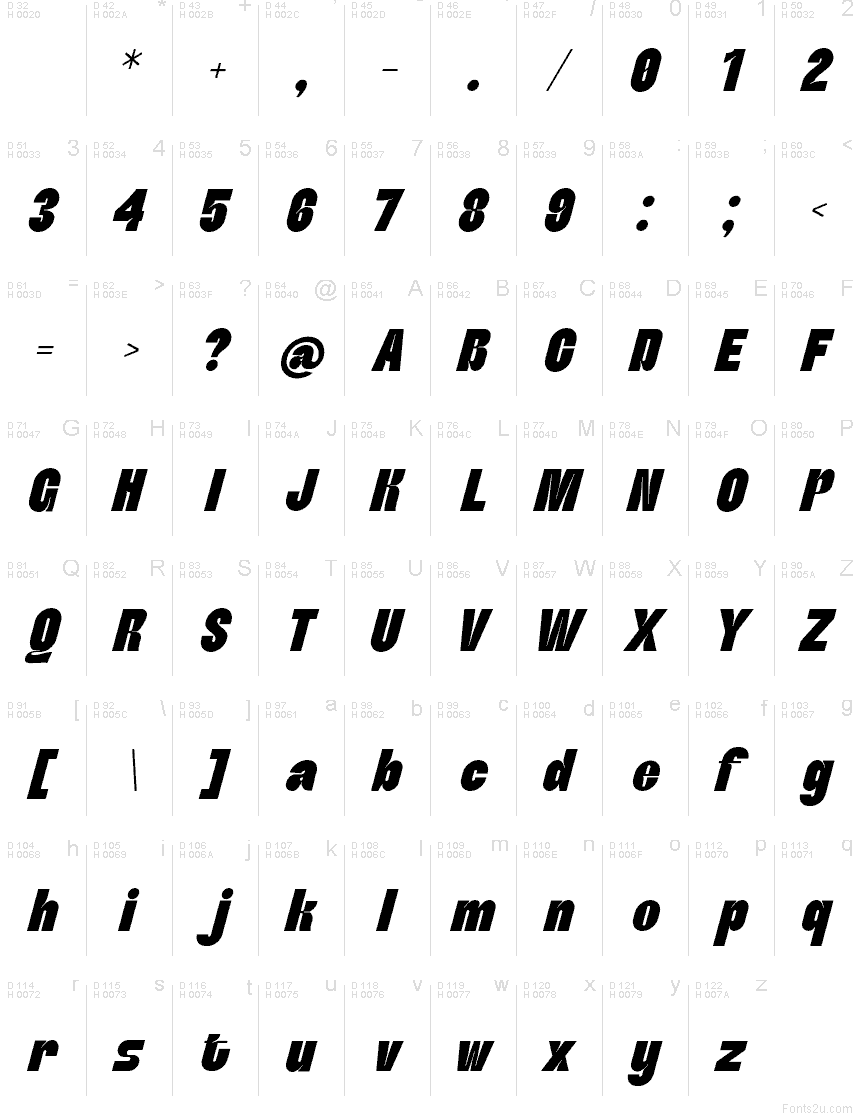
Monar Slant est une police de caractères italique moderne et gratuite, créée par Afkari Studio, caractérisée par des formes denses et dynamiques. Ses traits épais et son inclinaison tranchante créent un rythme rapide, très mode, tandis que les minuscules arrondies apportent de la souplesse à l'ensemble.
Utilisez cette police gratuite pour le branding streetwear, les pochettes d'albums, le graphisme sportif, les titres éditoriaux, les affiches d'événements et les textes courts. Ses formes compactes et penchées sont idéales pour les titres où le mouvement et le poids doivent porter le message.